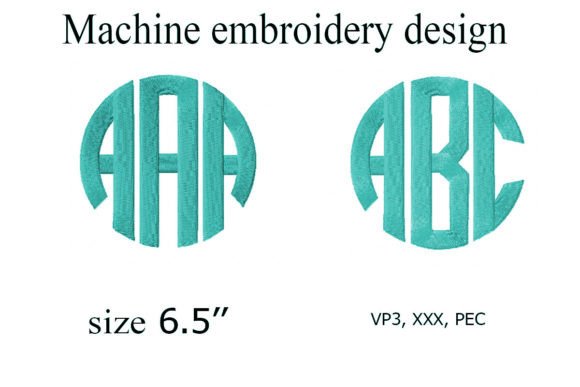
Circle Monogram
Если вы ищете высококачественные ресурсы, такие как Circle Monogram, этот премиум-пакет — фантастический выбор для ваших творческих проектов.